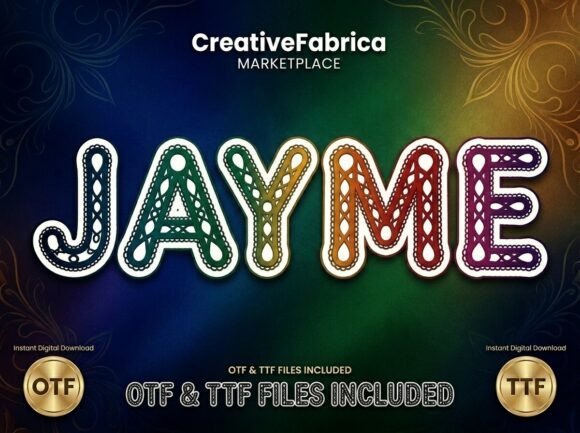
Jayme
قد يكون العثور على عناصر التصميم المناسبة أمرًا صعبًا، ولكن Jayme يقدم مجموعة استثنائية ترتقي بعملك على الفور.
سواء كنت تقوم بإنشاء منتجات الطباعة عند الطلب أو دعوات الزفاف أو رسومات وسائل التواصل الاجتماعي، فإن Jayme هو الخيار المثالي.